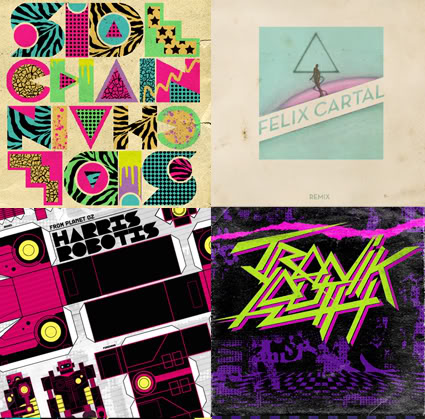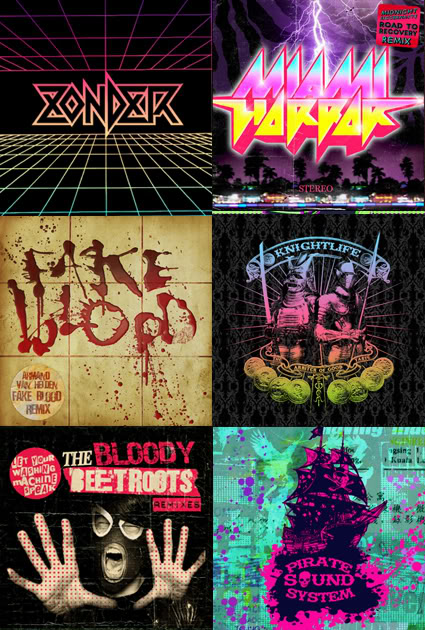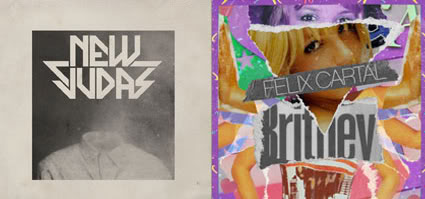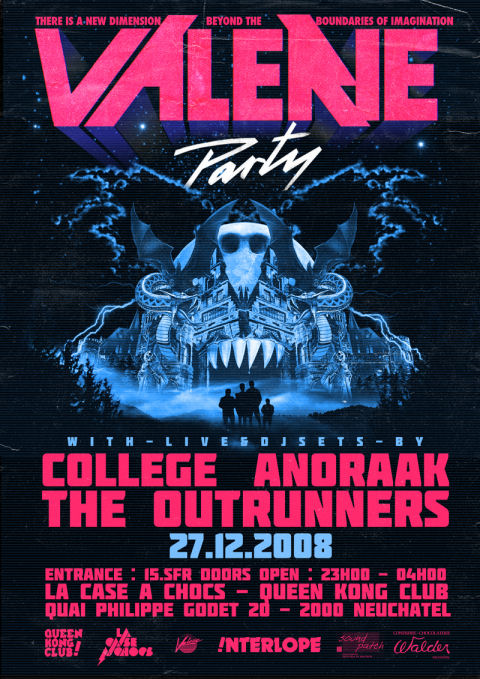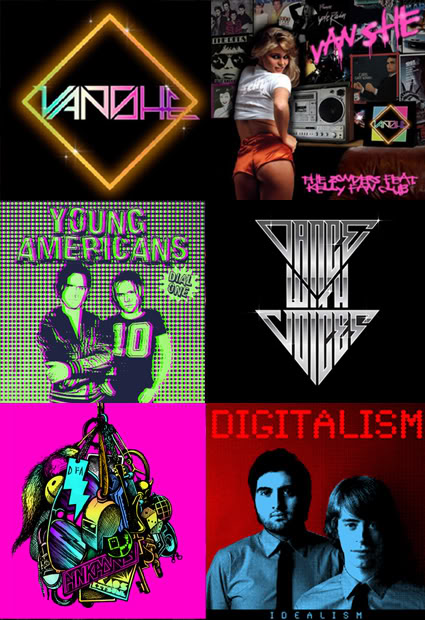
Suche diese eckige/schnittige Schrift bzw. Stil
gibt es fertige Schriftarten in die Richtung:
Oder muss man "normale" eckige nehmen und die dann selbst anpassen?
Wie nennt man den Stil überhaupt?
Mach' selber. Dann kannst Du das schön auf das Wort/die Worte anpassen.
Solche Metall-Band-Schriftzüge wurden meist extra gezeichnet. Es gibt einige daraus abgeleitete Freefonts, wenn ich mich recht erinnere hat Ray Larabie so etwas bei seinen frrüheren Schriften dabei (einfach mal selbst bei myfonts.com suchen). Bei Valene hat wohl die Avant Garde (mit Alternativformen) Pate gestanden. Solche Fonts wie bei Digitalism gibt es hunderte, das passende Suchwort ist Dot Matrix. Futura taucht bei mehrerenDeiner Beispiele auf. HipHop-/Gafiti-Fonts würd ich bei Blambot suchen. Harris Robotis so etwas ist auch nicht selten, man kann das aber leicht selbst erreichen, wenn man bei einer extrafetten Schrift seiner wahl mit Vektorgraphikprogramm die Punzen wegklickt. Pirate Sound System und Knightlife sind wahrscheinlich Thunderbird. Für die verdreckten Schriften sind die passenden Suchwörter grunge, distorted, eroded.